Seguro que la primera opción de tipografías de baseball que se te viene a la mente es la fuente de los Yankees, un emblema que ha trascendido la barrera de lo deportivo para convertirse en uno de los iconos más conocidos por la cultura popular a nivel mundial, según Albat.
Así como ellos, son varios los equipos que usan esta tipografía desde tiempos inmemorables. Si bien la letra de los Yankees es de las más solicitadas en el mundo del diseño gráfico, al ser de autoría propia, no se encuentra disponible para descargar en línea.
Esto no significa que sea la única en todo Internet, existen algunas fuentes de béisbol similares a la de los Yankees que puedes utilizar en todas tus piezas. Si bien son comúnmente llamadas letras beisboleras, puedes usarlas para darle una dosis de originalidad a todos tus proyectos de diseño gráfico.
Si te gusta el baseball, te habrás dado cuenta que las tipografías de las principales ligas del mundo tienen un punto en común: los textos que aparecen impresos son de tipo script, es decir, su estilo es muy parecido al de la escritura a mano.
Además, este estilo se extiende al resto de los elementos del deporte como la pelota y el uniforme. Lo cierto es que el script de las fuentes de letras beisboleras le agregan cierta calidez y tradicionalismo a cualquier diseño.
Por eso, en este artículo te mostraremos una gran lista de tipografías de béisbol que pueden darle ese toque especial a tus diseños. La mayoría de estas letras tipo baseball son gratuitas, así que podrás ampliar tu catálogo de fuentes de manera sencilla. Simplemente, elige las que más te gustan y adecúalas a tu concepto.
1. San Andreas
La descripción de esta tipografía es "letra beisbolera" sin más vueltas. Se trata de una de las tipografías baseball por excelencia. Esta fuente es de tipo script e incluye mayúsculas y minúsculas, así como algunos caracteres especiales.
Este detalle no es menor, ya que en muchas ocasiones se necesita agregar algún que otro elemento que complemente el texto en el logotipo o el diseño en general. Por fortuna, casi todas las fuentes de béisbol cuentan con caracteres adicionales para complementar tus creaciones.
2. Krinkes
Esta tipografía de baseball se caracteriza por su versatilidad, de modo que se pueden incluir elementos que acompañen las letras, tal como lo mencionamos anteriormente. Esta fuente de béisbol trae consigo mayúsculas, minúsculas y caracteres especiales. Además, la encontrarás disponible en los estilos regular y bold.
De esta manera, puedes adaptarla a diversos tipos de espacios y diseños. Recuerda que puedes usar estas fuentes de letras beisboleras en diseños que no son exclusivamente dedicados al deporte. ¿Te imaginas el nombre de una bebida con la tipografía Krinkes?
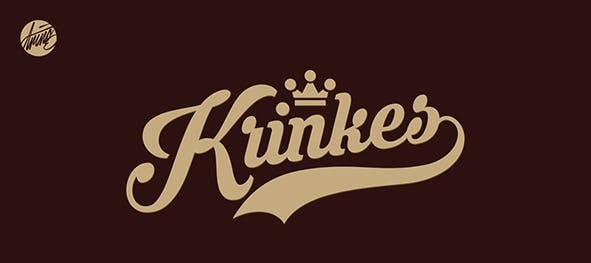
3. Painter
Esta tipografía de baseball tiene una vibra muy marcada, pues da la impresión como si hubiera sido delineada a mano. Por tal motivo, es una opción perfecta si de letras beisboleras hablamos. Incluye mayúsculas, minúsculas, así como algunos caracteres especiales. ¿La imaginas en tus diseños?
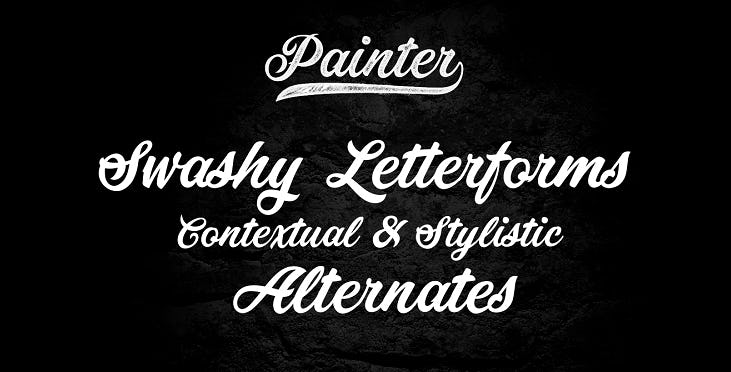
4. Brannboll
Esta tipografía es de las mejores opciones de letras beisboleras. Sí, el balón ilustrado dice claramente que esta es una tipografía de baseball creativa.
Se encuentra disponible en dos estilos y en mayúsculas, minúsculas y ligaduras. Incluso, esta fuente de letras beisboleras te podría servir para crear tipografías para logos de marcas urbanas.
5. Funkies
Funkies es otra de las tipografías de baseball con toques vintage que no solo se vería bien en algún jersey, sino también en algún logotipo. De hecho, es una fuente similar a la tipografía de los Yankees.
Se encuentra disponible en un solo estilo e incluye mayúsculas, minúsculas y algunos caracteres especiales. Un plus que ofrece esta tipografía de béisbol gratis es su borde coloreado. Puedes jugar con este detalle y el resto de tu diseño para crear una propuesta original e irrepetible.
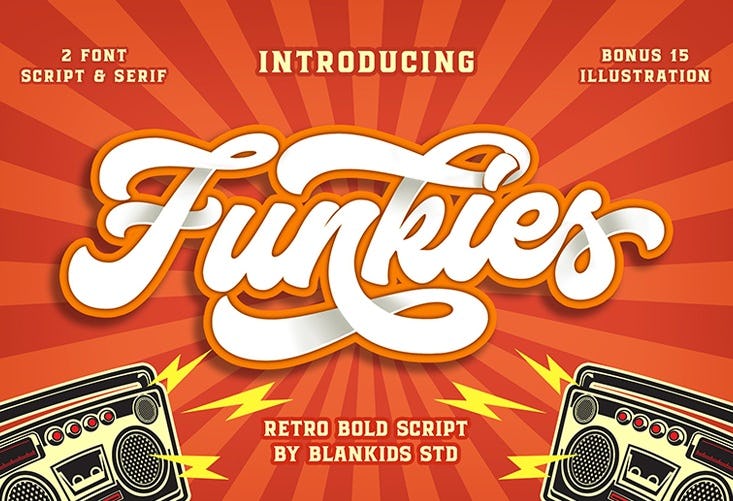
6. Headster
¿Quieres más tipografías vintage de béisbol? Pues Headster es otra de las fuentes de baseball que cumple con esta característica. Eso sí, esta fuente solo incluye mayúsculas y minúsculas. Sin embargo, es lo suficientemente versátil como para ser acompañada de algunos elementos gráficos o números. ¡Verás que se adaptarán muy bien!
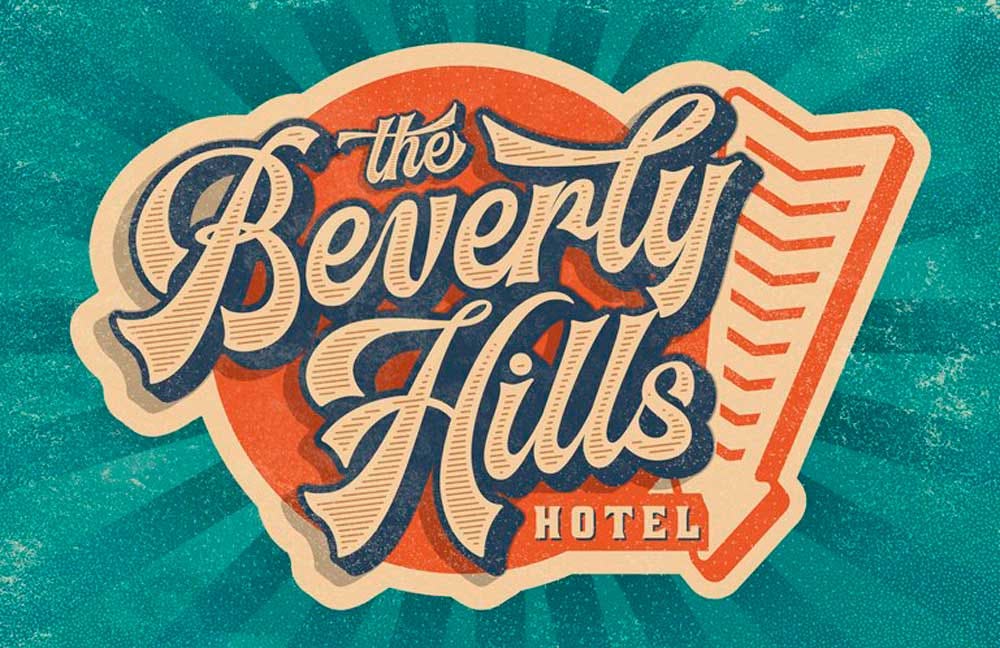
7. Lacosta
Puede que el nombre de esta tipografía de béisbol te recuerde al de una marca famosa de ropa, pero no tiene nada que ver con dicha compañía. De hecho, sus estilos son totalmente distintos.
Esta tipografía de baseball es simple y legible, de tal manera que podría quedar bastante bien en cualquiera de tus diseños. Podrás descargarla en dos estilos que incluyen mayúsculas, minúsculas y algunos caracteres especiales.
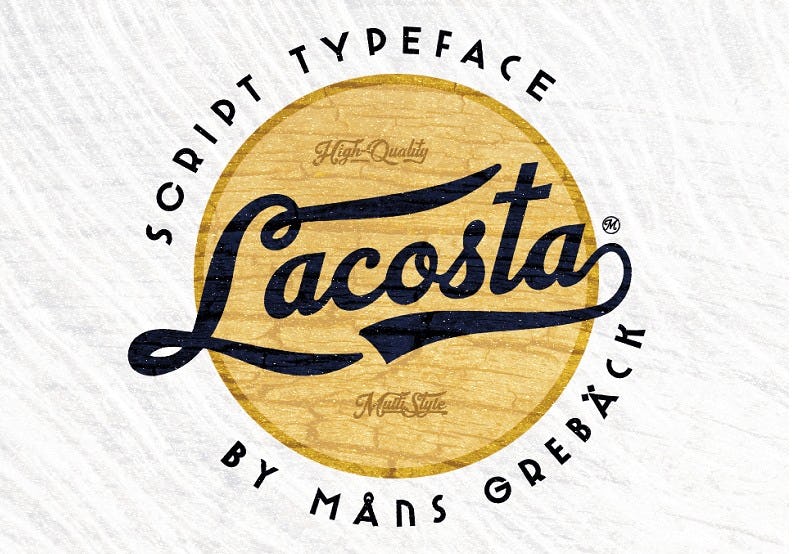
8. Auckland
Esta es otra de las tipografías de baseball que destaca por ser simple y directa, factores que te permitirán comunicar el mensaje a la perfección. Si bien su diseño es un tanto minimalista, se vería muy bien en jerseys o flyers relacionados con este deporte. Contiene mayúsculas, minúsculas, números, así como ligaduras, una característica de este tipo de fuentes caligráficas.
9. Cosmoball
La fluidez es la característica por excelencia de esta letra beisbolera. Creada por el diseñador Wacaksara, esta fuente de estilo manuscrito no sólo caería bien en jerseys o diseños que tengan que ver con el baseball, sino también en diseños que tengan que ver con restaurantes.
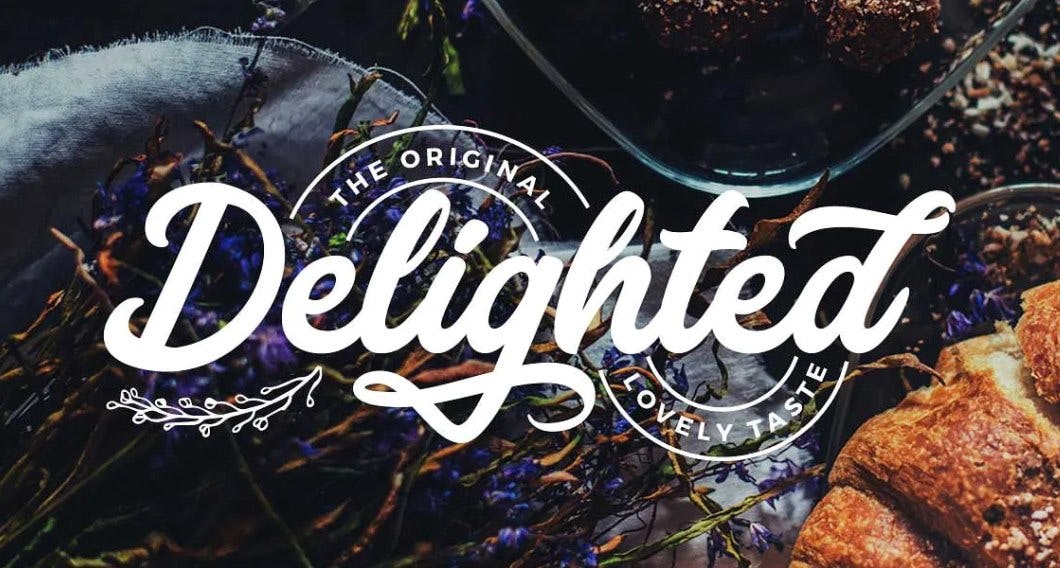
10. Megattor
Otra de las características de las tipografías de baseball es la extravagancia y con Megattor estará asegurada. Se trata de una tipografía de béisbol que sobresale por su audacia, un factor perfecto si lo que estás buscando son fuentes que vayan bien con los deportes. Esta letra beisbolera iría muy bien en pósteres y, por supuesto, en jerseys de baseball.
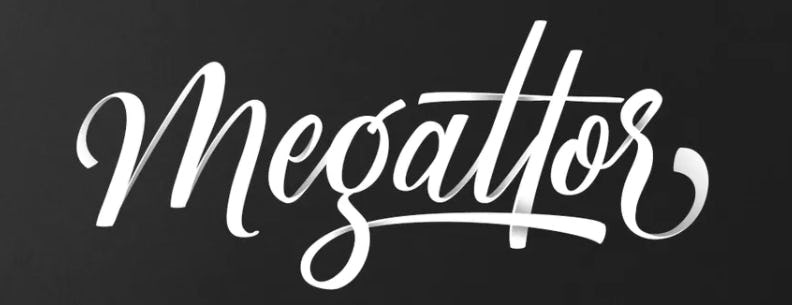
11. Agistha
Agistha es una tipografía de baseball que tiene un aspecto de tipo graffiti. Este último detalle podría hacer pensar que se sacrifica en legibilidad, pero todo lo contrario, pues sus trazos son lo suficientemente simples como para incluir la letra en camisetas, sitios web o pósteres.
Además de incluir mayúsculas, minúsculas y números, contiene hasta 99 caracteres alternativos y ligaduras.
12. The Brands
The Brands es una tipografía de baseball de DaFont con una legibilidad envidiable. Se trata de una gran alternativa no solo para camisetas, sino también para logos o flyers deportivos. La encontrarás disponible en mayúsculas, minúsculas y ligaduras para darle ese toque único y especial a tus diseños.
13. Blessed
Si eres seguidor del baseball estadounidense, habrás notado que esta letra beisbolera se asemeja mucho a la tipografía de los Dodgers gracias a su estilo sutilmente cursivo. Esta fuente de baseball es también una gran alternativa de letra para títulos. La descarga de esta fuente solo incluye mayúsculas y minúsculas.
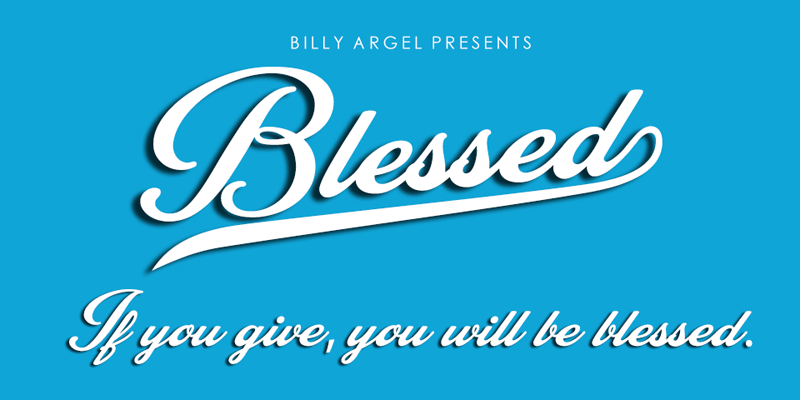
14. Brannboll NY
Si la fuente anterior te hace recordar a los Dodgers, esta es una de las opciones que más se asemeja a la tipografía de los Yankees, incluso en los colores que se muestran en la imagen de prueba.
Esta tipografía de béisbol es similar a la que mostramos más arriba, aunque guarda detalles únicos como sus ligaduras. Además, incluye mayúsculas, minúsculas y algunos caracteres especiales.
15. Altamonte
Esta tipografía de baseball es una clara muestra de que la audacia también puede transmitir tranquilidad. Altamonte es una letra beisbolera versátil por naturaleza, por lo que se podrá adaptar fácilmente a cualquiera de tus proyectos, incluso sin que estos tengan que ver con el baseball o los deportes.
Asimismo, esta fuente de baseball puede ser muy útil para rubros como el cine y las series. ¿Acaso no te recuerda a un póster de película? Anímate a usarla en donde quieras.
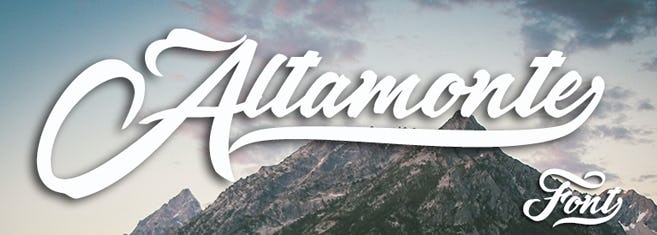
16. Grandes
Si bien la legibilidad no es su fuerte, esta tipografía de béisbol ha sido especialmente creada para atraer miradas, de manera que su uso ideal debería ser con algunos puntos extra para cumplir su cometido.
Como su nombre lo dice, si se configura esta fuente de baseball a un buen tamaño, tu diseño llamará la atención sin ninguna duda. Disponible en mayúsculas, minúsculas, números y algunos caracteres especiales.
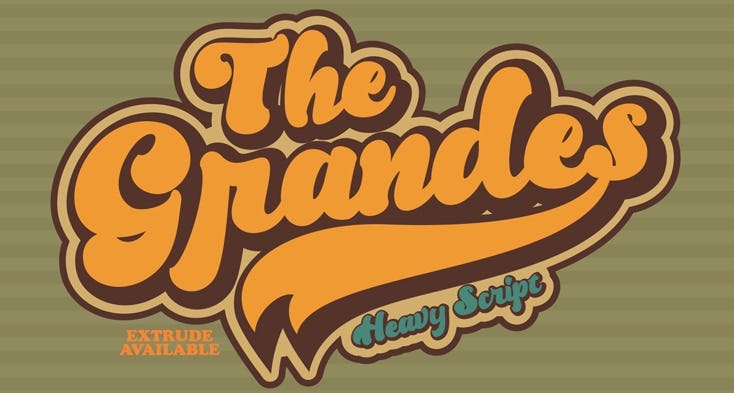
17. Ederson
Nuevamente nos encontramos con un tipo de letra de béisbol con una pinta retro bastante marcada. Se trata de una letra beisbolera que se vería bastante bien en camisetas y en pósteres. La encontrarás disponible en mayúsculas, minúsculas, ligaduras y algunos caracteres especiales.
18. Euphoria
El estilo cursivo de Euphoria también nos recuerda rápidamente a la tipografía de los Yankees. Esta fuente de baseball sobresale por sus perfectos trazos que no sacrifican la legibilidad, lo cual la convierte en una gran alternativa para camisetas, flyers y pósteres. Disponible en mayúsculas, minúsculas, ligaduras y caracteres especiales.
19. Sebastiana
Si al ver esta tipografía de béisbol lo primero que se te viene a la mente es playa y palmeras es porque el diseñador logró su objetivo. Transmite una vibra relajada, alegre y deportiva.
Sin embargo, entre las ligaduras que trae se incluyen las que no tienen diseño, lo cual aporta sobriedad sin sacrificar la audacia. Así, Sebastiana es otra de las grandes alternativas de tipografías de baseball con una gran dosis de originalidad. Incluye mayúsculas, minúsculas y ligaduras.
20. Wannabees
Esta fuente de baseball es cursiva, así que tiene una ligera similitud con la tipografía de los Yankees. Sin embargo, a diferencia de las anteriores, Wannabees tiene trazos mucho más sencillos y no muestra una ligadura como tal, sino una línea simple. La encontrarás disponible en mayúsculas y minúsculas.
21. Team Spirit
¿Recuerdas ese logo de Nike vintage? Esta fuente de baseball está súper inspirada en el ámbito deportivo más allá del béisbol en sí. Para usarla sólo debes descargar y modificarla de la manera que más te convenga en tu programa de diseño preferido.
Al ser una tipografía simple, puedes complementar el texto con alguna bajada de tipo san serif y te quedará espectacular.
22. Vintage Party
Si tu marca reúne no sólo el espíritu deportivo de una fuente de letras beisboleras, sino también combina los principios de los años 70, la Vintage Party es justo la tipografía que estabas buscando.
A diferencia de las fuentes de baseball anteriores, no cuenta con ese renglón por debajo del texto, sino que contiene un borde que rodea toda la palabra, por lo cual puedes jugar con el diseño a tu gusto.
23. Struck Base
¿Recuerdas que mencionamos que no siempre debes usar estas fuentes beisboleras para diseños relacionados al deporte? Bueno, en este caso haremos una excepción porque la Struck Base está pensada justamente para este fin.
Aunque, por supuesto, también puedes usarla para un logotipo de una marca o como una guía para entregar un logo a un cliente que se relacione directamente con este rubro.
24. World Series
Si no te convencieron todas las otras fuentes de baseball que te compartimos antes, aquí te dejamos una opción súper refinada que definitivamente le dará un plus a tus diseños.
25. Moraline Script
Esta tipografía de baseball combina en la medida justa entre el aspecto tradicional con lo moderno. Pruébala con otras fuentes de estilo sans serif y juega con colores para sorprender a tus clientes.
26. Boston
Si estás buscando una gran fuente de letras beisboleras para usar en el diseño de camisetas para un equipo de béisbol, entonces Boston es ideal para ti.
Boston es una tipografía de béisbol que cuenta con caracteres en mayúsculas y minúsculas, en números y en una gran variedad de puntuaciones, así como tiene caracteres alternativos, un conjunto estilístico y ligaduras. Por eso, incluye tres fuentes de baseball que pueden ayudarte a crear diseños sorprendentes.
Como puedes notar, la fuente de béisbol de Boston también tiene una sombra gruesa, lo que la hace más atractiva a la vista. Asimismo, está diseñada para tener trazos elegantes y puede usarse para una variedad de propósitos de diseño, como logotipos y marcas.
27. Bandbox
La siguiente tipografía de baseball en nuestra lista es Bandbox, que es un tipo de letra de béisbol inspirado en los logotipos clásicos. De hecho, Bandbox es la mejor fuente de script de béisbol en negrita.
Lo que la hace diferente de otras fuentes de baseball es su forma de letra cursiva gruesa y fluida que es ideal para cualquier diseño relacionado con los deportes. Además de los 18 banners y las ligaduras atléticas que vienen con Bandbox, también hay otro plus que incluye la fuente.
Esta es también una de las mejores letras de béisbol editables para usar en logotipos, carteles y diseños de camisetas. De modo que si estás buscando una fuente de escritura de béisbol que puedas usar libremente como diseñador gráfico, entonces Bandbox es una excelente opción para considerar.
28. Swingman
Si eres un creativo que busca una fuente de escritura vintage perfecta para crear una variedad de diseños, entonces echa un vistazo al tipo de letra de béisbol Swingman.
Swingman es la mejor tipografía de béisbol vintage con 120 glifos, que incluye mayúsculas, minúsculas, números, puntuación, ligaduras y muchos caracteres alternativos.
Esta fuente está diseñada para tener una ligadura final extendida, lo que la hace más icónica y atractiva. De hecho, Swingman es una de las letras de béisbol más populares para camisetas, gorras y otras prendas relacionadas con el deporte del béisbol.
Entonces, si deseas utilizar la mejor tipografía beisbolera vintage para el diseño visual de una marca de ropa deportiva, no busques más, porque Swingman es una excelente alternativa.
29. Flanders
Otro tipo de letra imprescindible para el diseño de marca es Flanders, una tipografía de béisbol de escritura audaz y moderna.
Esta fuente es perfecta para diseñar un tema deportivo, un tipo de logotipo, citas, marcas denominativas, etc. Flanders incluye muchas características OpenType, como ligadura, alternativa estilística, alternativa contextual, swash, etc. Además, es compatible con varios idiomas.
Es una letra beisbolera complementaria que te permite crear un efecto de extrusión o sombra en un instante sin necesidad de ninguna herramienta de software gráfico. Además, Flanders se puede usar para etiquetas de productos, leyendas, diseño de camisetas y más.
30. Jawbreak
Este es un tipo de letra de béisbol que tiene tres estilos distintos y cortes alternativos. Jawbreak es una fuente de baseball moderna con bordes clásicos. De hecho, es una de las tipografías más versátiles que puedes tener como diseñador de logotipos y creativo en general.
Es perfecta para logotipos, marcas deportivas, carteles, diseño de indumentaria, titulares de revistas, etiquetas y mucho más. Jawbreak presenta un juego de caracteres Adobe Latin 1 completo, compatible con la mayoría de los idiomas occidentales, lo que la convierte en una tipografía de béisbol flexible.
Una característica que la diferencia de las otras letras tipo baseball es que esta fuente está diseñada para tener todas las letras mayúsculas, lo que la hace lucir más poderosa e ideal para diseñar nombres de equipos de béisbol.
31. Pitcher
Si trabajas para un equipo de béisbol o para clientes que desean tener un logotipo con un tema deportivo, entonces esta tipografía de béisbol es una excelente opción.
Pitcher es la mejor fuente de pincel en negrita ideal para logotipos de bares o equipos deportivos, etiquetas de cerveza o cualquier rubro en el que necesites un aspecto fuerte y sólido con mucho carácter.
Este tipo de letra de béisbol incluye varias características de OpenType, como ligaduras estándar y alternativas contextuales para conexiones fluidas entre letras. Puedes probar sus opciones de swash o titulación cuando necesites títulos más personalizados o cuando diseñes un logotipo.
Las ligaduras extendidas únicas y distintivas de Pitcher la convierten en una letra beisbolera idónea para usar como diseñador gráfico y de logotipos.
32. Buinton
Otra fuente imprescindible para todos los creativos, especialmente los diseñadores de logotipos, es este tipo de letra de béisbol Buinton. Tiene serifas al comienzo de los trazos, letras mayúsculas y un diseño formal, así como muchos caracteres alternativos, letras y ligaduras.
Buinton también tiene diferentes formas y anchos para darle un logotipo vintage o un aspecto deportivo a tu diseño. Además, es una fuente adecuada para usar en diseños de camisetas e ilustraciones editoriales.
De hecho, esta tipografía de baseball es considerada una de las fuentes más versátiles, lo que te permite diseñar elementos tipográficos hermosos, elegantes y diversos con ella.
Si buscas originalidad para tus proyectos, sin duda, estas tipografías de baseball te podrían ayudar para que tus diseños llamen doblemente la atención y logres un gran “hit” en la mente de tus espectadores.